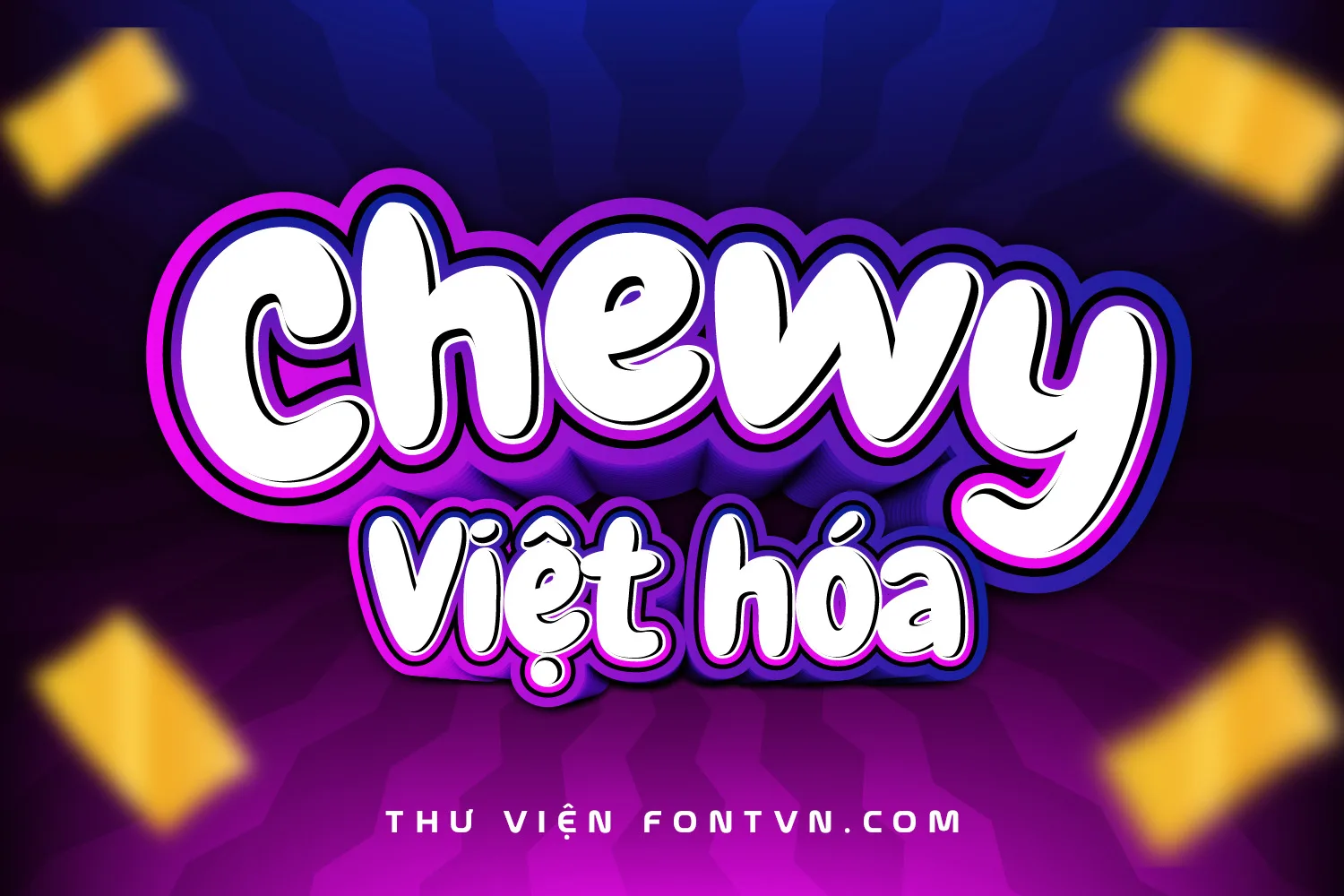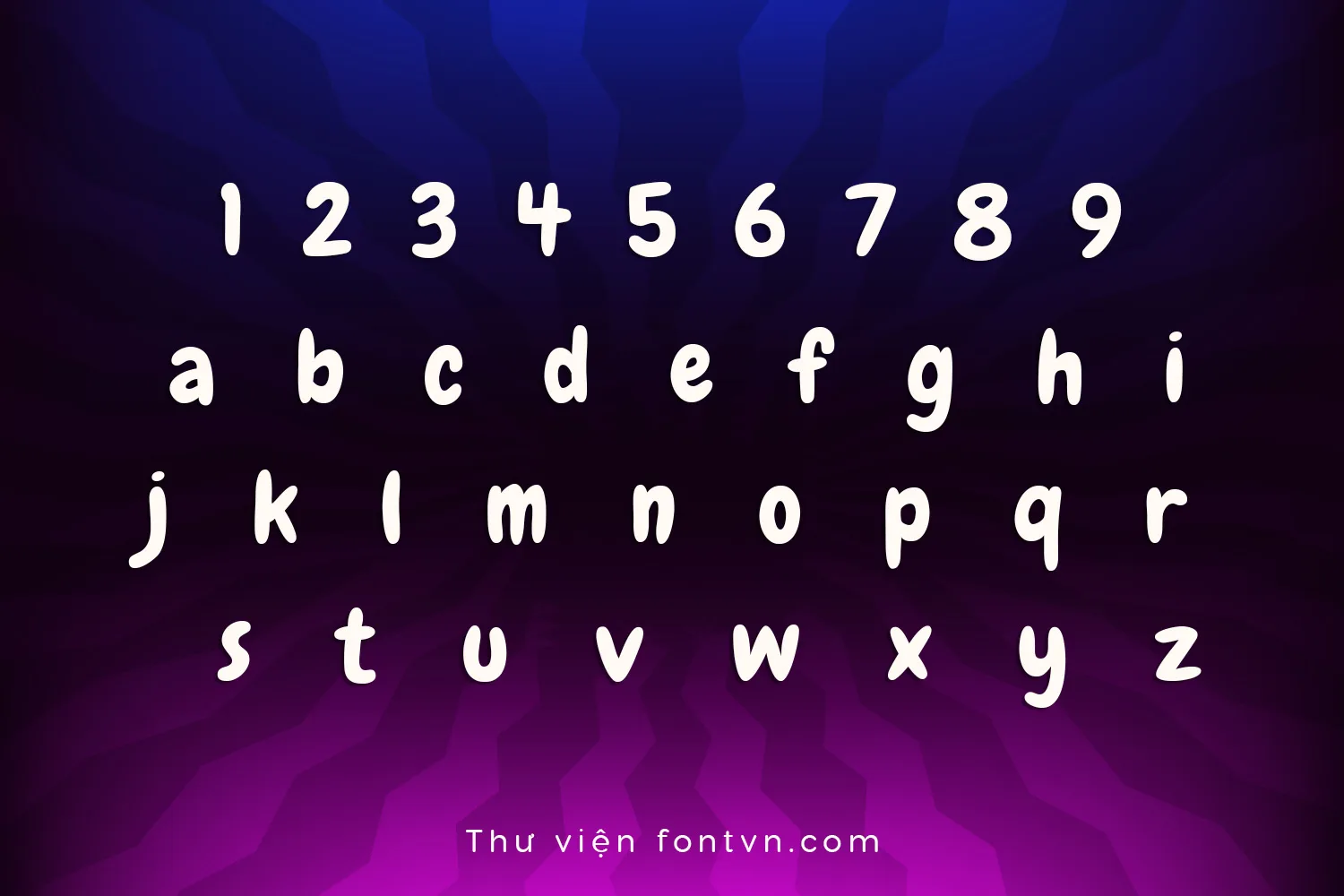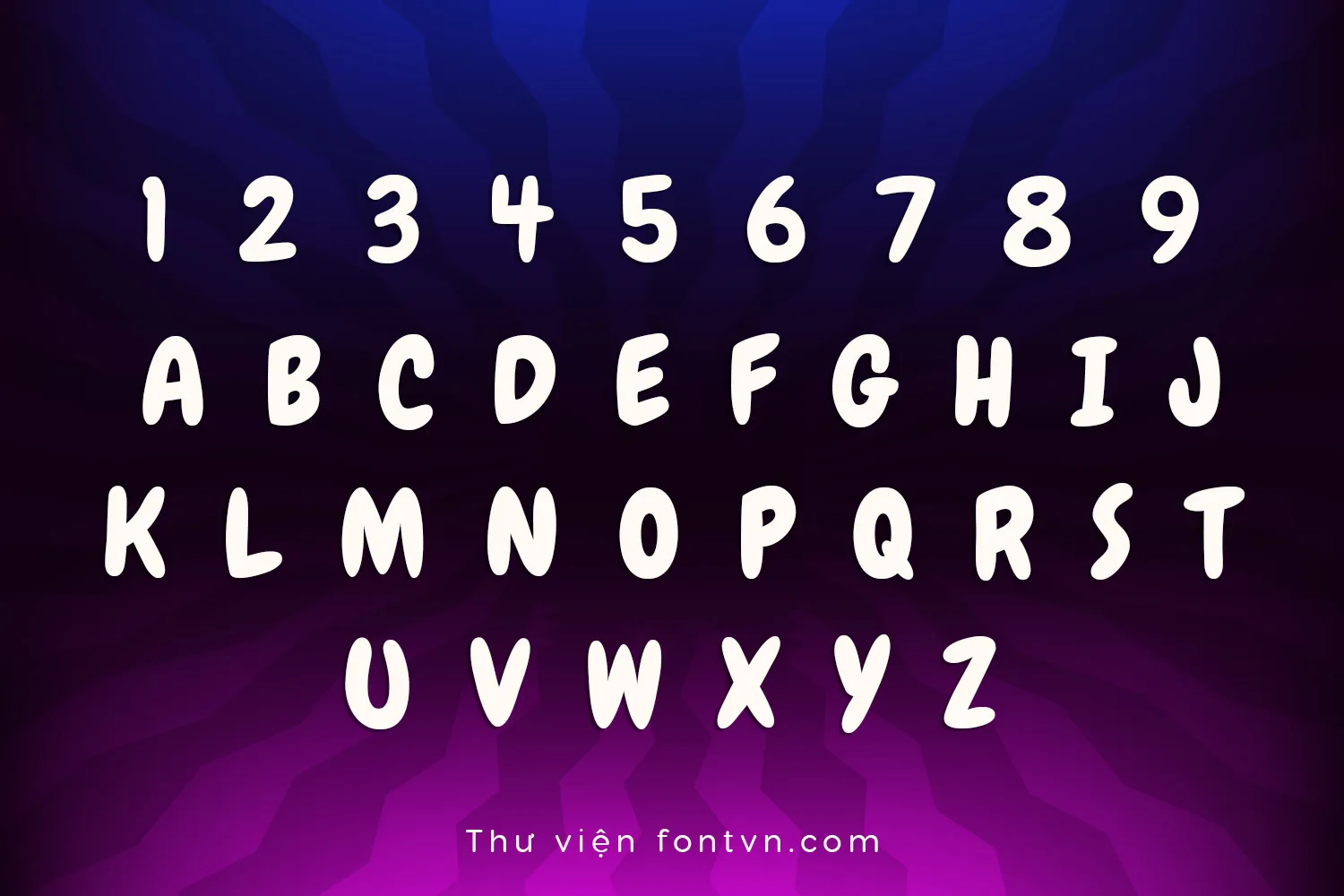
Chewy là một display font nổi bật với nét chữ tròn trịa, mềm mại và đầy năng lượng. Phong cách “kẹo ngọt” giúp chữ trở nên thân thiện, dễ đọc và gây ấn tượng mạnh ở phần tiêu đề.
Bản Việt hóa được tinh chỉnh cẩn thận, đảm bảo dấu tiếng Việt hiển thị hài hòa. Font rất phù hợp cho thiết kế bao bì, poster, banner quảng cáo và các dự án sáng tạo trẻ trung.
Chewy mang lại cảm giác vui tươi, ngọt ngào và dễ gây thiện cảm — lý tưởng để tạo điểm nhấn trong thiết kế.
Bản Việt hóa được tinh chỉnh cẩn thận, đảm bảo dấu tiếng Việt hiển thị hài hòa. Font rất phù hợp cho thiết kế bao bì, poster, banner quảng cáo và các dự án sáng tạo trẻ trung.
Chewy mang lại cảm giác vui tươi, ngọt ngào và dễ gây thiện cảm — lý tưởng để tạo điểm nhấn trong thiết kế.